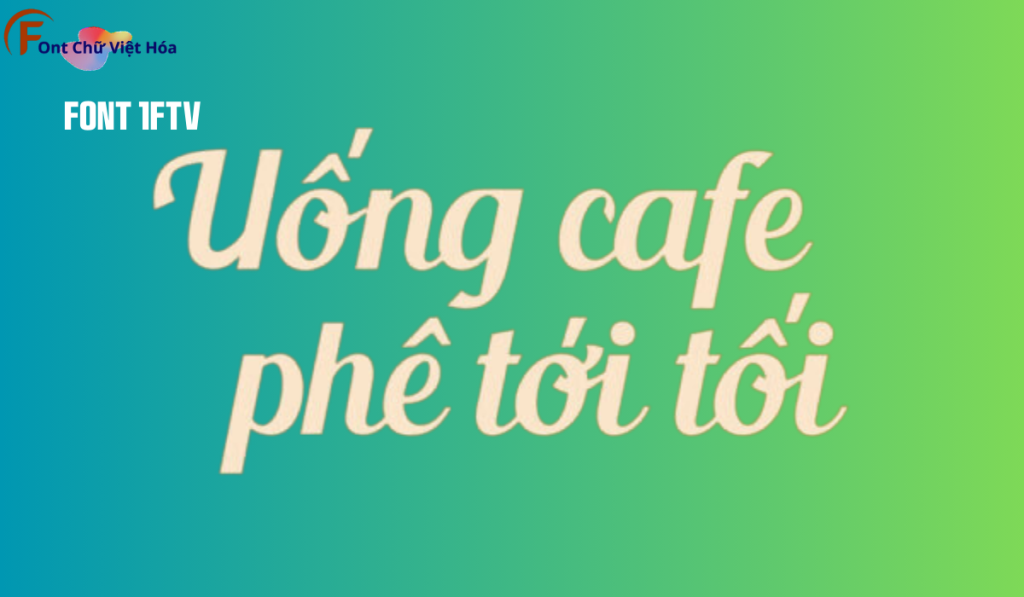
Font 1FTV Blenda Script
Kiểu chữ: Chữ thảo
Font 1FTV Blenda Script là một font chữ độc đáo, thuộc bộ 1FTV, nổi bật với phong cách script cổ điển và các đường nét đậm, mềm mại. Thiết kế của 1FTV Blenda Script tập trung vào sự thanh lịch và dễ đọc, đặc biệt phù hợp cho các thiết kế đòi hỏi tính thẩm mỹ cao như poster, logo, và tiêu đề. Với tỷ lệ chữ cân đối và các đường nét rõ ràng, font này tạo ra ấn tượng thị giác mạnh mẽ và giúp tối ưu hóa không gian trong thiết kế. Font này cũng đã được Việt hóa, mang đến sự linh hoạt và tiện dụng cho các dự án thiết kế bằng tiếng Việt.